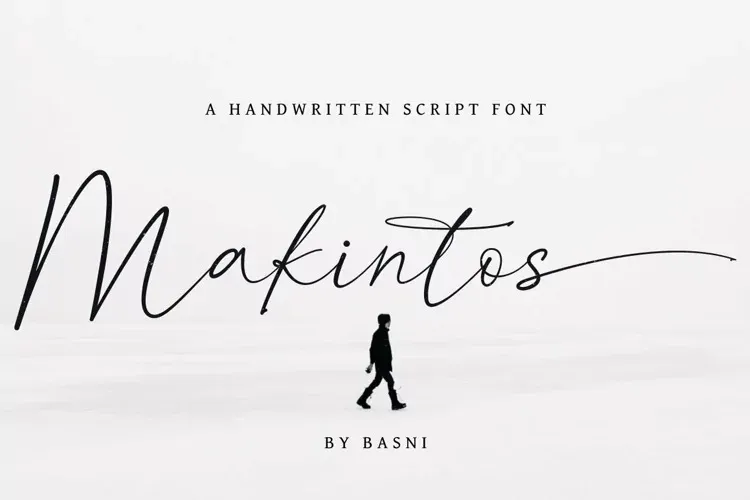
Makintos Font – Fonte Grátis
Makintos Font
A fonte Makintos é uma elegante escrita clássica criada pela Basnistd. Perfeita para aplicações variadas como sinalizações, identidades corporativas, sites, rótulos de vinhos e até mesmo projetos editoriais. Disponibilizamos a fonte Makintos em uma categoria especializada nas fuentes script da 99designs. Makintos apresenta todos os caracteres maiúsculos e minúsculos, suporte multilíngue, ponto final, ligaduras de início e fim além de outros recursos. Tudo isso está à disposição dos designers através de software que suporta OpenType. Esta fonte é perfeita para quem busca uma escrita fluida e sofisticada para seus projetos. Seja você um designer de sinalização, criando identidades corporativas modernas ou realizando trabalhos editoriais, Makintos atenderá suas necessidades. Seu design elegante combina bem com qualquer estilo de projeto e sua variedade de caracteres torna-a uma escolha sólida para qualquer aplicação visual.